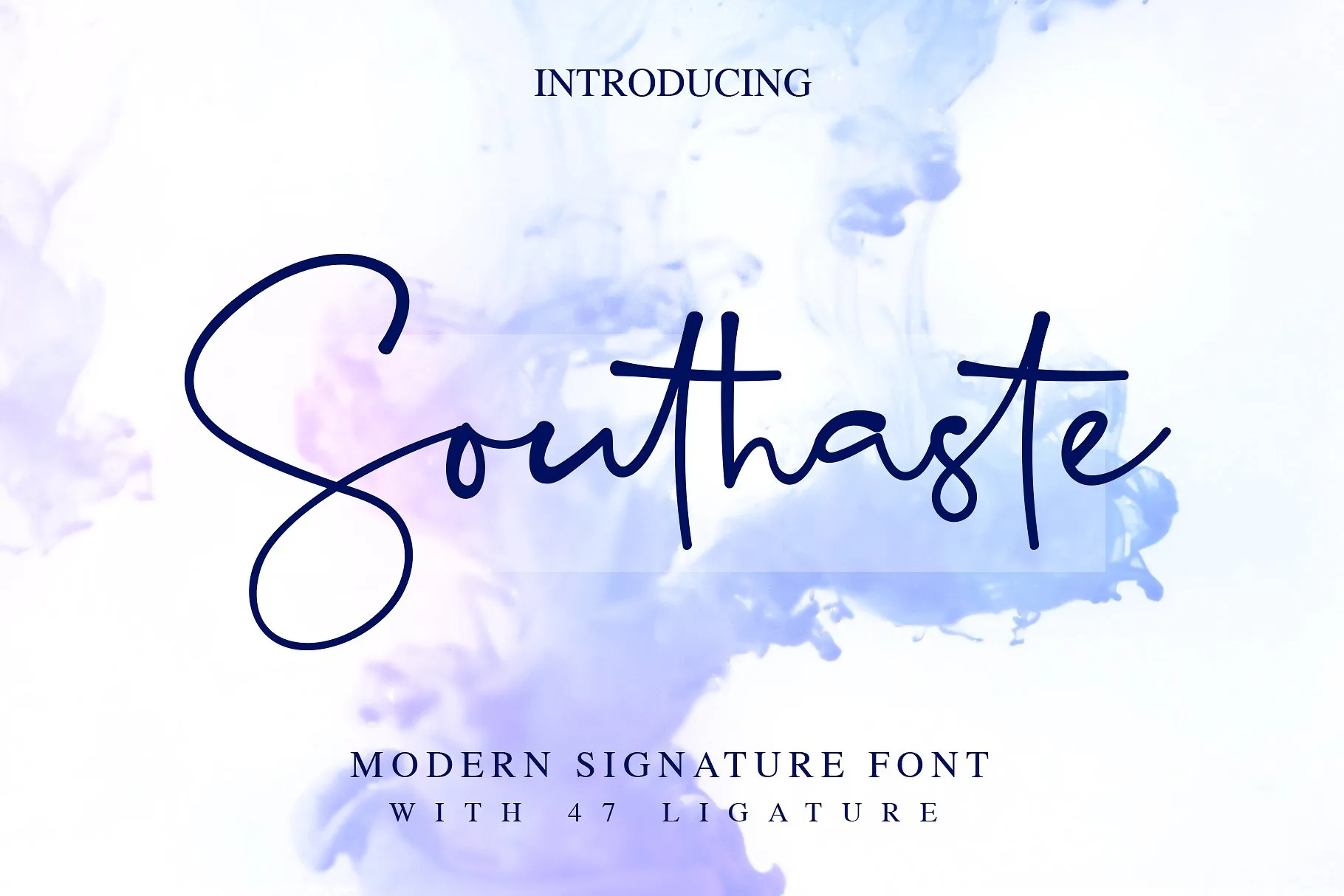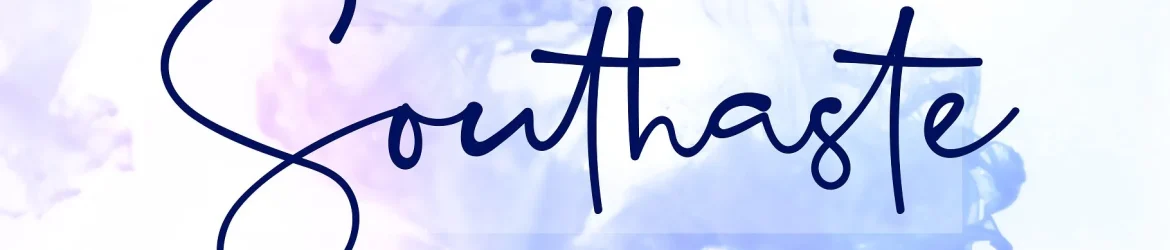
Southaste Signature Font – Download Grátis
Agradecemos pela atenção! Introduzimos uma nova fonte de assinatura moderna. Quer dar um toque autêntico à sua criação? A Southaste é perfeita para seus próximos projetos criativos, como marcas nas fotografias, assinaturas ou logomarcas da assinatura, citações, capas de álbum e cartões de visita. Seja de cartões de visita até marcas nas fotos, a Southaste está aqui para enriquecer o seu trabalho em um nível superior. A Southaste – uma fonte de script com estilo simples e moderno é perfeita para aqueles que desejam dar aos seus designs um toque único e autêntico.